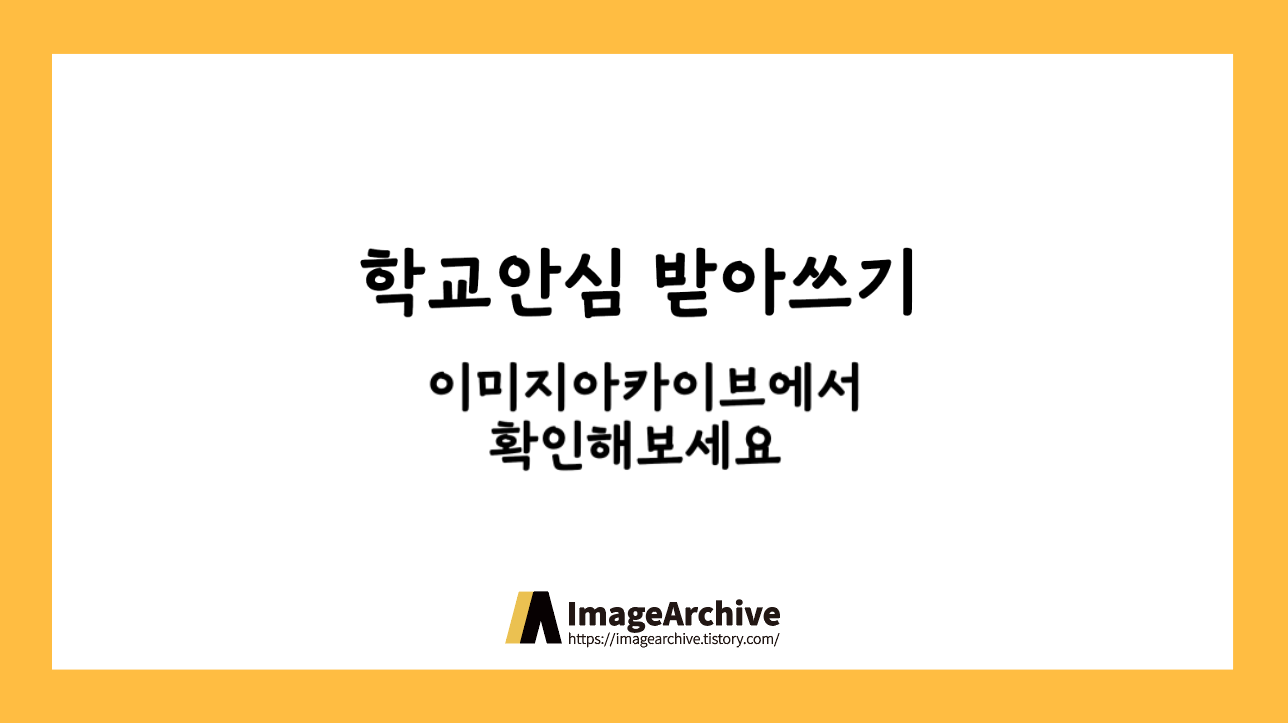
학교안심 받아쓰기
'학교안심 받아쓰기체'는 학생들의 학습 환경을 고려하여 개발된 폰트입니다. 이 폰트는 받아쓰기와 같은 교육 활동에서 학생들이 글자를 명확하게 인식하고 따라 쓸 수 있도록 돕기 위해 만들어졌습니다.
형태적 특징
이 폰트는 손글씨의 자연스러움과 디지털 글꼴의 정갈함을 조화롭게 담고 있습니다. 글자 모양은 부드러운 곡선과 균형 잡힌 자간을 특징으로 하며, 가독성을 높이기 위해 일정한 획의 두께와 간격을 유지하고 있습니다. 이러한 디자인은 학생들이 글자를 쉽게 읽고 쓸 수 있도록 도와줍니다.
사용용도
'학교안심 받아쓰기체'는 교육 자료, 학습지, 교과서 등 교육 관련 문서에 특히 적합합니다. 친근하고 따뜻한 느낌을 주기 때문에 어린이 대상의 동화책, 포스터, 초대장 등에서도 효과적으로 활용될 수 있습니다.